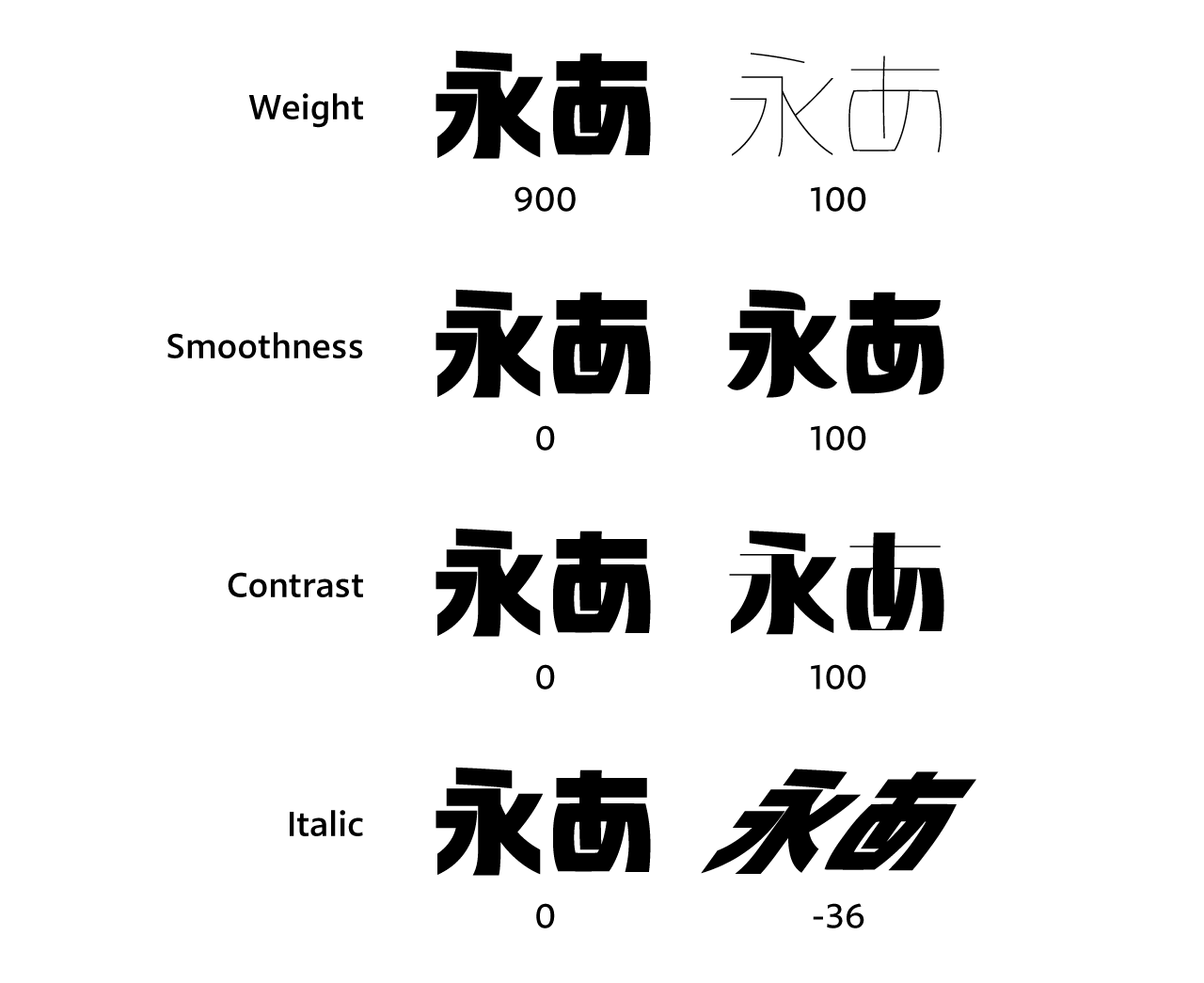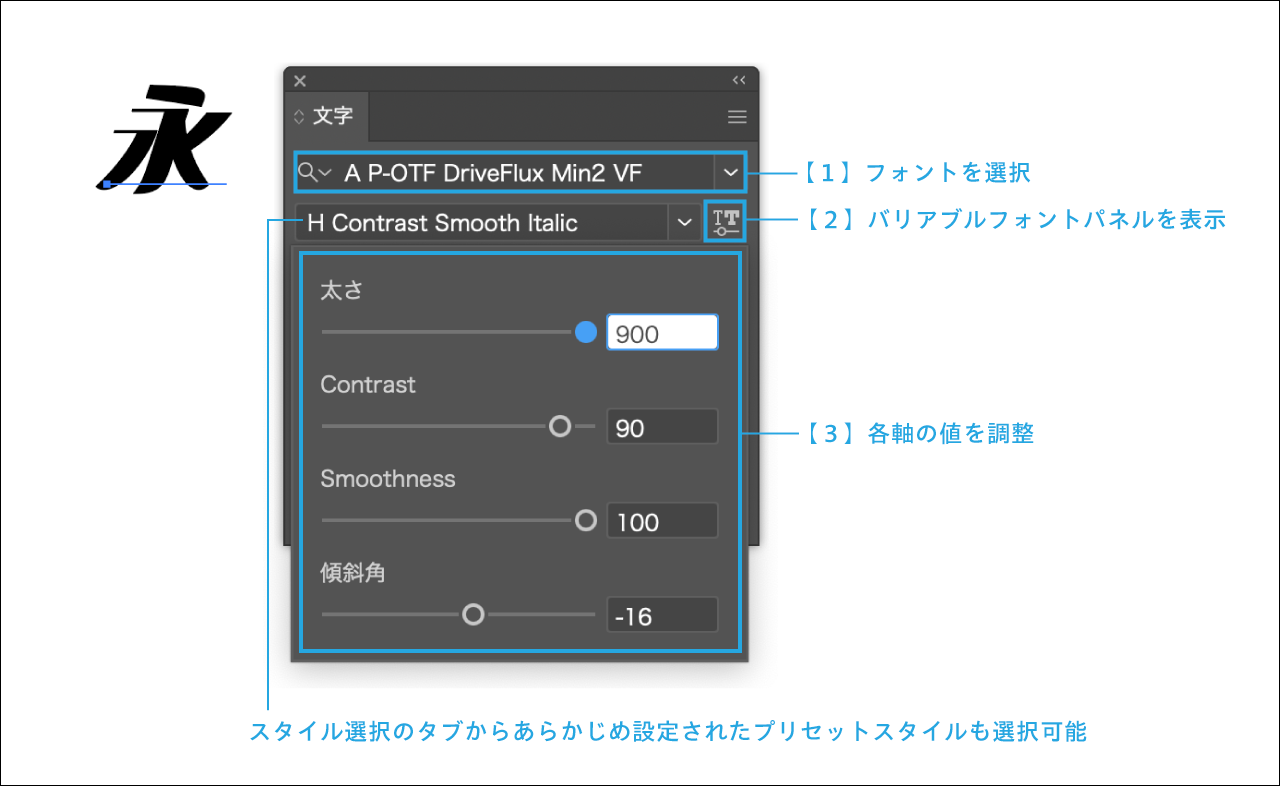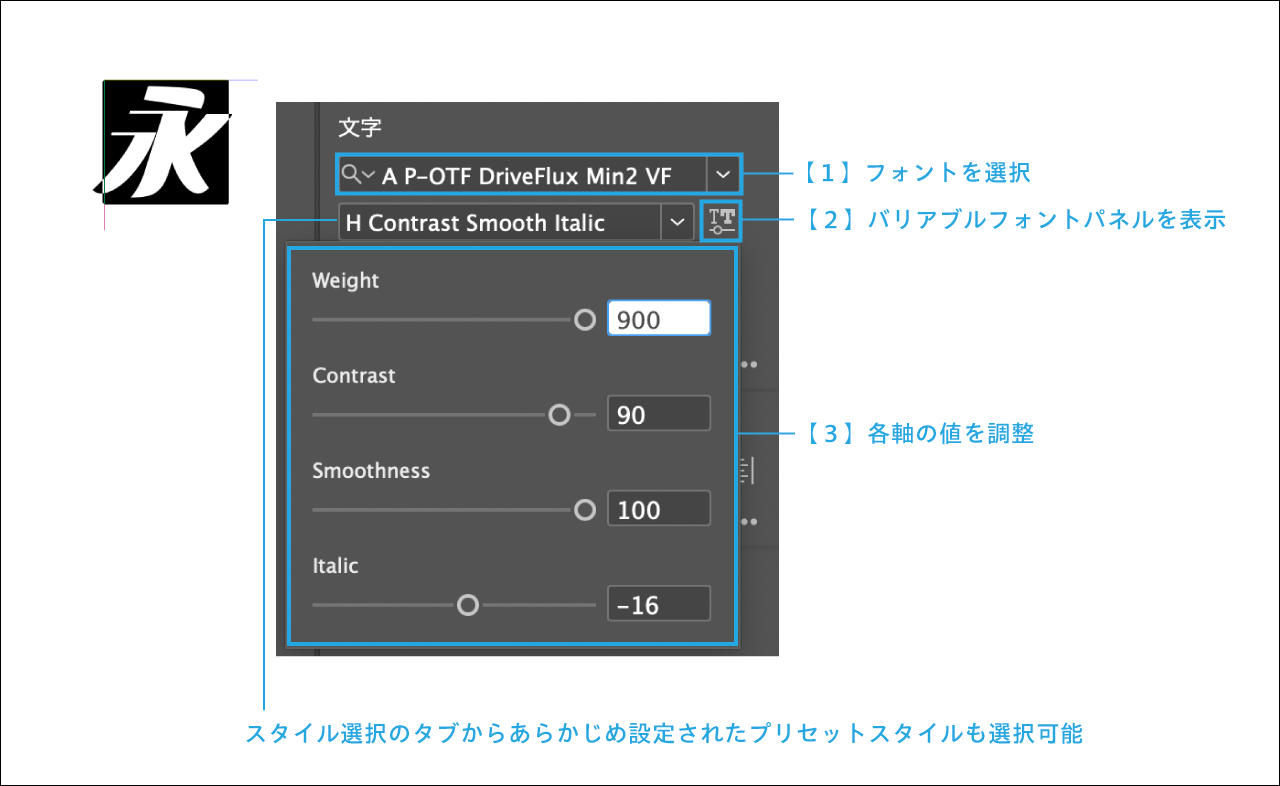
DriveFluxについて
DriveFlux(ドライブフラックス)とは、オンスクリーン用(PCやスマートフォンなどの画面表示用)に開発された4つの可変軸をもつ和文書体のバリアブルフォントです。可変機能を活かし、幅広いデザイン表現ができます。
バリアブルフォントとは
バリアブルフォントは、可変機能が搭載されたフォントです。1つのフォントファイルに複数の原型デザインを内包し、それらを動的に補間処理することで、多様なデザインを柔軟に生成できます。
可変軸について
それぞれのデザイン軸を横断的かつ無段階に選択できるため、表現したいイメージに調整ができます。
Weight(ウエイト)軸:太さを100~900の間で調整
Smoothness(スムースネス)軸:エレメントに流線型のカーブデザインを0~100の間で調整
Contrast(コントラスト)軸:主に横画の太さを0~100の間で調整
Italic(イタリック)軸:傾斜角を-36~0の間で調整
左:Weight:900 / Smoothness:0 / Contrast:0 / Italic:0 を基準としています。
右:基準から1軸ごとに最小値/最大値を指定しています。
プリセットスタイルについて
あらかじめ各軸の値が設定された36スタイルの中から選択することもできます。